撇号
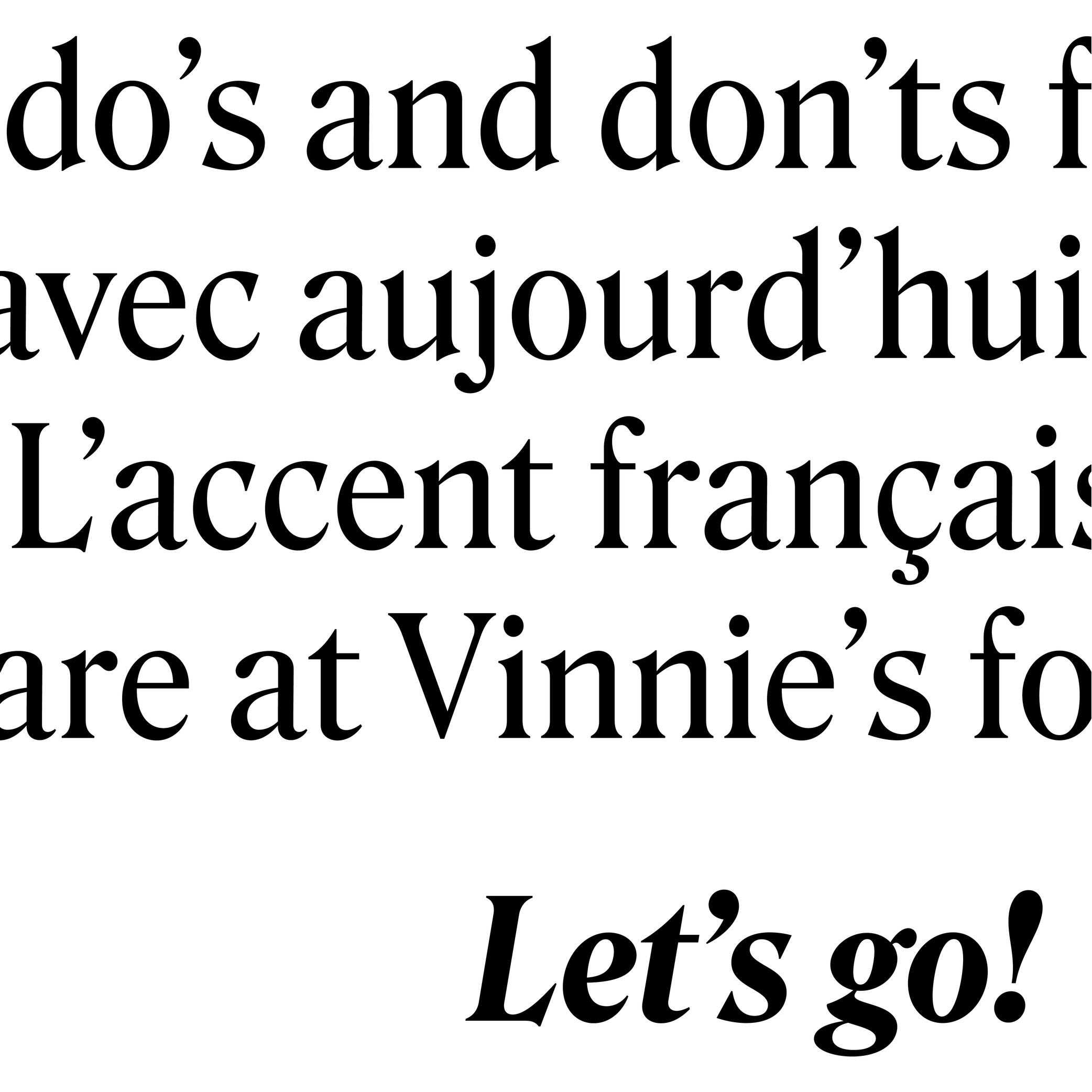
撇号(apostrophe,在英语中也用作单引号)是使用拉丁字母的语言中非常常见的标点符号。它在不同的语言中有不同的功能。例如,在英语中,撇号可用作所有格(“part of a letter” 变成 “a letter’s part”)或省略标记(“it is”变为 “it’s”)。
类似撇号造型的符号可追溯到 16 世纪的法国,当时雕刻师乔弗瓦·托里 (Geoffroy Tory,1480–1533年) 引入了这个符号来代替一个字母或短词。
随着打字机的发明,其他类似的字符形(单引号、角分号、尖音符等)被组合到与撇号相同的按键中,以便在有限的键盘空间内节省按键数量,但这导致了现在仍然存在的混淆,角分号经常被错用作撇号。
设计精良的字体中的撇号往往会设计成倾斜或弯曲的造型(和字体中的逗号设计相关),以避免与角分号混淆。
APOSTROPHE(撇号): U+0027
RIGHT SINGLE QUOTATION MARK(右单引号): U+2019
MODIFIER LETTER PRIME(修饰角分号): U+02B9